深圳 TypeSchool 才刚刚结束,3type 即将在北京携手汉仪字库和 Type is Beautiful,为大家带来为期一周的中文字体设计课程。
字体作为一门视觉语言向我们传达了许多超越文本的信息,承载字体的媒介在不断迭代更新,而字体的变化和创新也从未停止过。并非每个人都想要做一整套中文字体,然而文字设计在各领域的应用却是不胜枚举。商业标识、导视系统、公共领域、艺术创作、编辑出版、个人品牌形象……字体排印(typography)都是视觉传达的重要基石。通过系统学习汉字字体设计,你也会对汉字的笔画和结构等原理建立更加清晰的认识,显著提高文字相关的平面设计水平。
3type 的中文字体设计课程,从本土需求出发,经过两年的实践积累与总结,逐渐发展出自己的课程架构:从零基础开始,一步步教你认识汉字;理解汉字背后的文化;了解中文字体设计的历史;体验手工绘制字稿的过程;由浅入深掌握汉字的基本结构与设计手法;入门专业的字体设计软件,并借助专为汉字设计优化的 Glyphs 软件学习 OpenType 以及字体编程等高级功能。除了科学的造字方法,我们还准备了 3type 独家 TypeKit 大礼包、以及一系列字体文化讲座、复刻字体工作坊等环节,课程末尾还有最强大脑与像素眼竞赛等丰富多彩的活动。
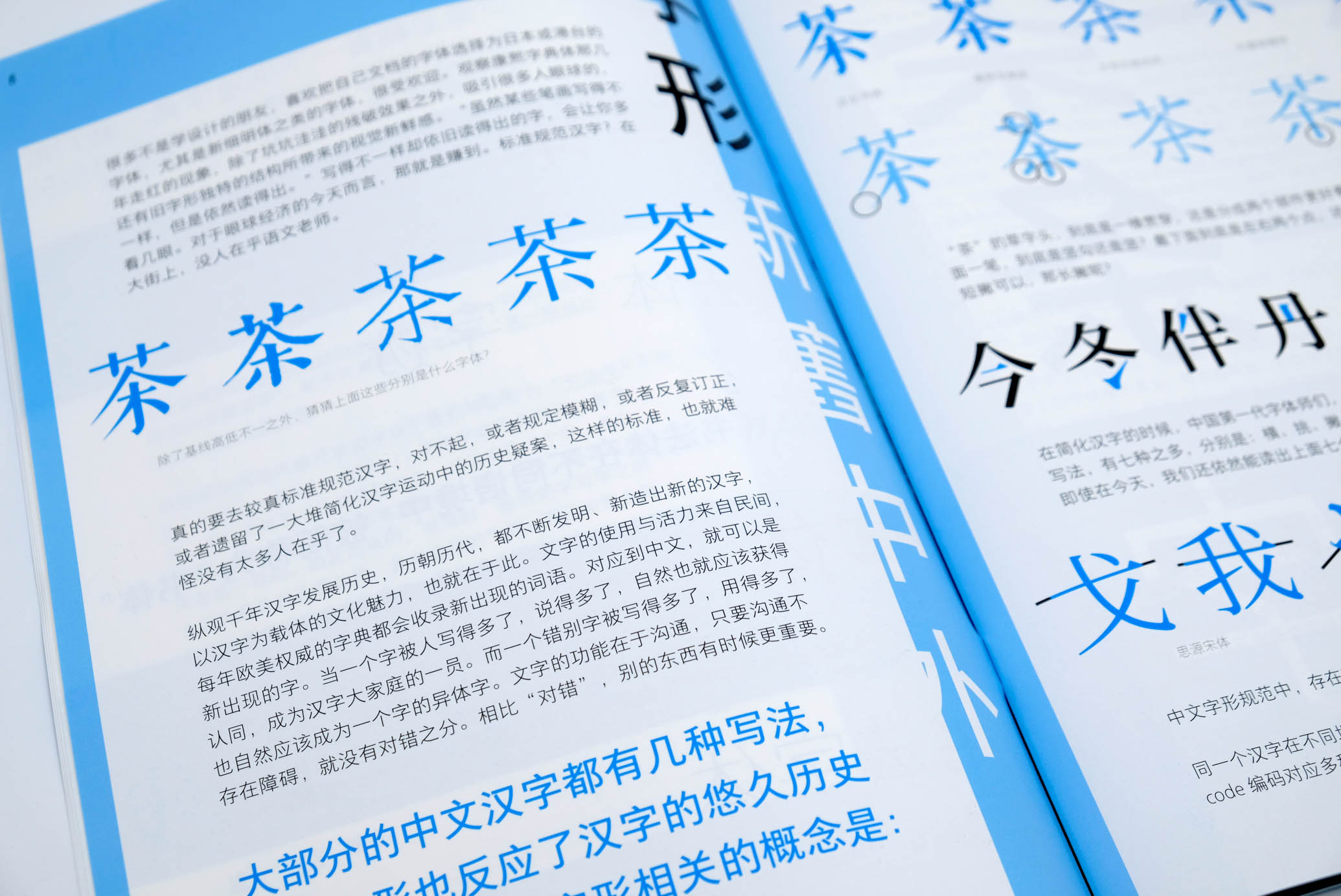
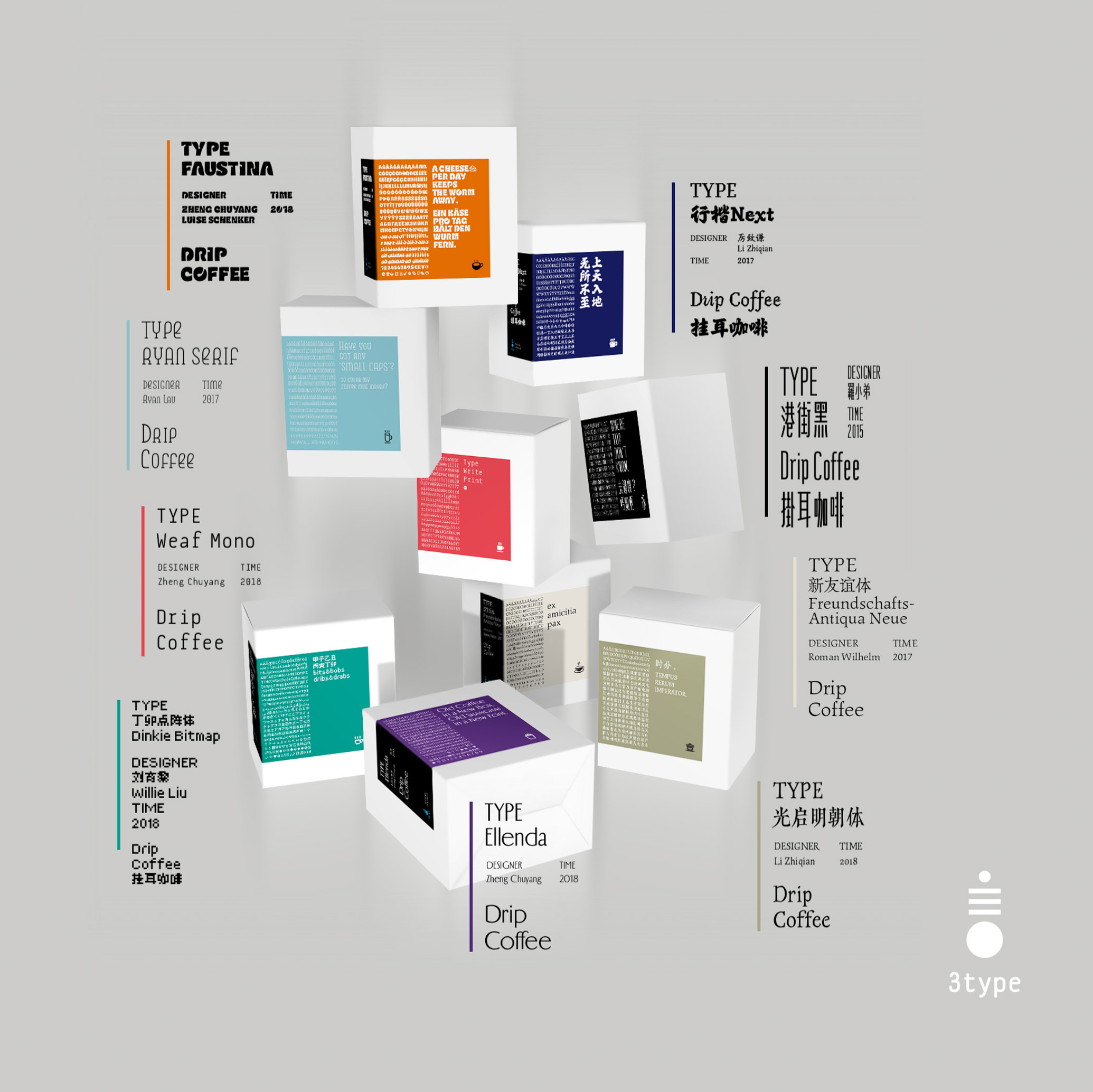
中文字体的这些问题,你想过吗?
如何透彻理解中文字形结构,正确选择合适的字体?
中文印刷字体的发展史,对当今数字字体有何影响?
宋、黑、仿、楷的字形特点怎样应用于实践?
复刻字体是如何创作的,对字体设计的意义是什么?
字面、轮廓、中宫、第二中心线……这些概念是什么,又该如何调整优化?
设计原创中文字体,该从哪里入手?
中文字体的西文部分应当如何匹配设计?
如何利用 Glyphs 软件优势开发中文字体?
中文字库制作是否有捷径可走?
中文排版如何设置看起来才是舒适的?
TypeSchool 和汉仪字库资深设计师朱志伟老师和刘宇老师,将为你一一释疑解惑,带着你走出原创字体的第一步,而对于有志参加「汉仪字体之星」的同学来说,此次课程更是一条不可多得的捷径。课程结尾更有人气主播 Éric Q. Liu 为大家带来久违的 TypeSchool 经典环节「文瀛讲坛」,此次加量版「文瀛讲坛」聚焦于中文排版,将大家在平时的工作和创作中可能遇到的字体排印相关问题一网打尽。
朱志伟老师 1971 年至 1991 年在北京外文印刷厂从事印刷活字雕刻工作,1996 年开始涉⾜字体设计,有多项字体设计作品成功开发为字库产品在社会上广泛使用,同年在日本森泽公司举办的国际印刷字体竞赛中「北魏楷书」获得铜奖,1999 年「铁筋隶书」获得该项赛事的评审委员奖。 2015 年加盟汉仪后设计开发「汉仪玄宋」,任职汉仪字库艺术总监、汉仪字体之星设计大赛评委, 并被北京服装学院设计学院聘为客座教授。
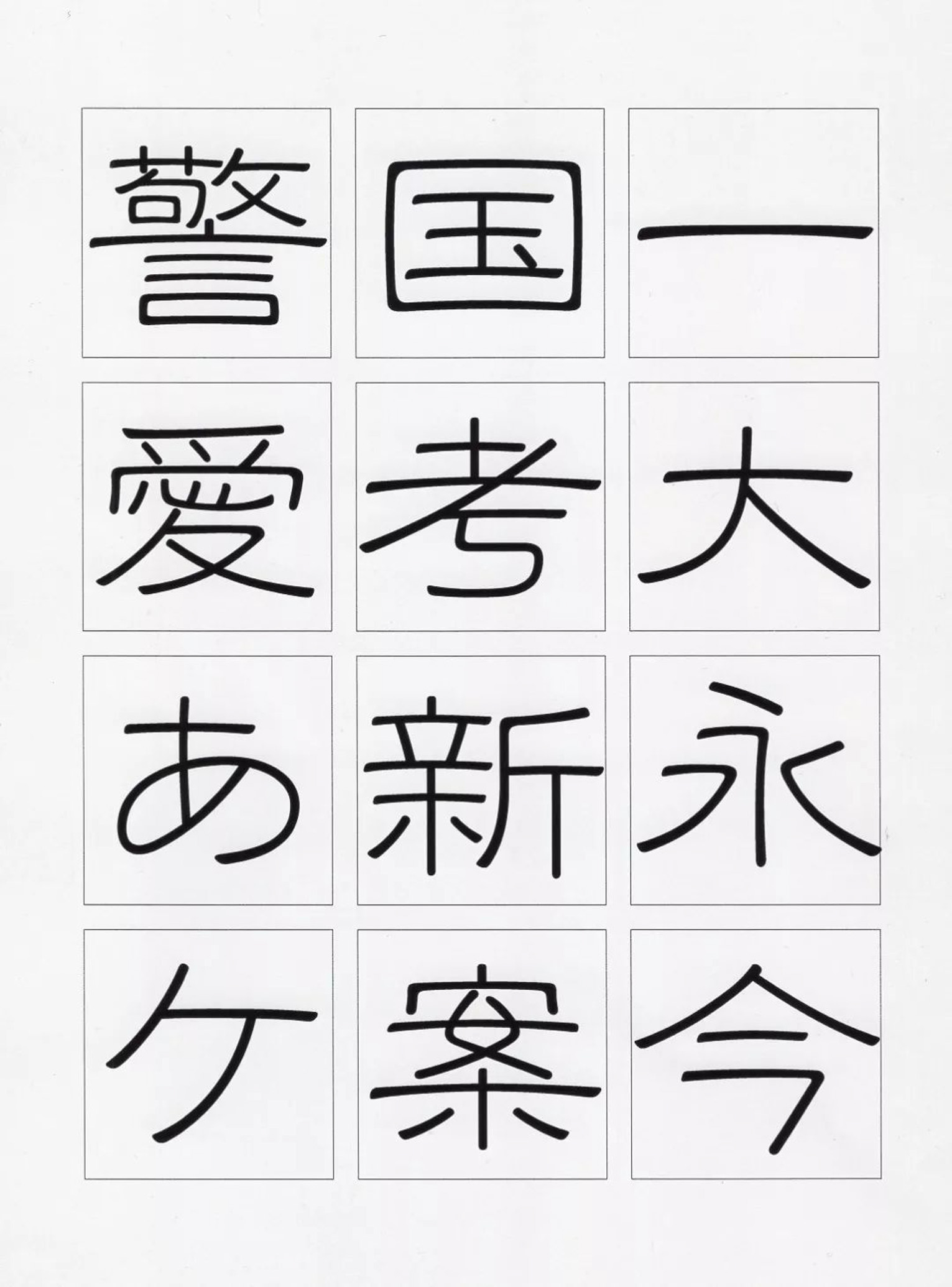
此次 TypeSchool 朱志伟老师将以多年行业经验和敏锐的眼光,帮助大家迅速掌握中文设计的要点,并有针对性地进行辅导。
刘宇毕业于北京服装学院视觉传达专业,现任汉仪公司高级定制项目组组长,同时身为SGDA 深圳市平面设计协会会员,ATypI 国际字体排印协会会员。刘宇曾负责多个定制字库项目,先后在阿丽达黑体定制项目、芬兰 Supercell 公司皇室战争游戏字体定制项目中任职中文主创设计师。先后创作了汉仪力量黑、汉仪跳跳体、汉仪乐喵体、汉仪帅线体、汉仪夏日体等字体。乐喵体推出后立刻引发了下载风潮,当年便荣获小米年度最受欢迎字体奖。在刷屏时代,为了满足市场越来越强烈的个性化需求,刘宇不断用创新字体丰富着视觉的表达。
凭借多年字体设计的经历,刘宇将会给大家带来更多激发字体设计创意的思路,以及如何从身边的方方面面寻找可以借鉴到自己设计中的灵感。
郑初阳是 3type 联合创始人之一,德国德绍包豪斯设计硕士,曾就职于欧洲顶尖的品牌设计公司 MetaDesign,服务过多家跨国公司。郑老师擅长在多文化语境中的开展平面与品牌设计,对多语言字体具有多年的研究与实践经验。
杨林青,著名旅法书籍、平面设计师,从事当代出版物的策划、编辑与设计工作,并致力于中西文字体的媒介应用和图形信息交流的研究。曾多次获得“中国最美的书”奖,第七届和第八届全国书籍设计艺术展社科类、文学类、教育类最佳书籍设计奖,2017 年年度亚洲卓越新闻奖“SOPA 卓越杂志设计奖金奖”。曾策划和参与《字体传奇——影响世界的 Helvetica》《平面设计中的网格系统》中文版的出版。2017年主编与设计《中文字体应用手册》。
杨老师可谓是 TypeSchool 的老朋友了,连续几年的中西文字体课都来做过讲座。这次我们有幸再次请到了杨老师,他在百忙之中将为我们带来「作为语言的设计」的讲座,解析中西文字体的选择、应用、建立系统、再到表达内容主题。同时杨老师还会跟同学们密切互动,从一个书籍设计师的角度,给出自己对于字体的独到见解。参与的同学们,可别忘记提前准备好杨老师的字体书请他签名哦!
Eric 在 Type is Beautiful 开设了关于中文排版的「孔雀计划」专栏,每篇洋洋洒洒一两万字,巨细靡遗地逐一分析目前排版的细节问题,逼死各种强迫症。这次「文瀛讲坛」中,Eric 不仅会亲自给大家划重点,还会从理论分析落实到大家日常的排版实践。字库的 OpenType 特性从哪里调用?使用 InDesign 和 Illustrator 进行中西文排版需要做怎样的设置、又有哪些技巧?一段 CSS 代码的利弊将要如何权衡?……种种问题,将带大家逐一解决。
大家平时用 Adobe 软件做排版,可无论 InDesign 还是 Illustrator,里面都是险象环生,稍不留神,就会一脚踏入大坑!Eric 已经将那些最让人头大的问题整理成了「InDesign 中文排版五大原则」让大家从此无惧深坑困扰!
如果没有电脑,平面设计师怎么工作?怎样编排字体?怎样在版面里插入图片?怎样运用色彩?设计稿做完了又如何让印刷机批量印刷?
今日,绝大部分的设计靠计算机软件完成,得益于它的迅捷,也受制于它的单一,更因为行业知识的断层,数字工具成为我们唯一的依赖。当我们渴望探索新的创作手法,当我们深入研究某种风格的来源,当我们意识到设计师与工艺材料之间的隔阂,当我们争论 AI 是否能代替创意工作者,当我们开始思考人的设计与创作活动的本质……我们无可避免地频频回望,期待从历史中寻找启迪。
这也许是纪录片 Graphic Means(《平面之道》)在去年一经推出就引起广泛反响的原因。这部有关前数字时代西方平面设计历史的纪录片,从上世纪五十年代直至九十年代、从热金属铸排机到激光照排、从手工剪贴到数字 PDF 文档,它探索了平面设计职业生产方式的发展。此次课程将与纪录片制作方合作,将它正式带到你的眼前。
第一天,全面了解中文字体设计的基本流程,临摹经典中文字体——宋体;
第二天,学习中文字体设计的理论知识,亲自动手做汉字间架结构的练习,临摹经典中文字体——黑体;
第三天,继续学习中文字体设计基础知识、创意字体的设计方法并绘制草稿,初识字体设计软件 Glyphs;
第四天,进一步学习 Glyphs 软件,在软件中绘制临摹的宋体黑体字并导出;著名书籍设计师杨林青将通过「作为语言的设计」与学员分享对字体设计的真知灼见。
第五天,完善自己的设计,学习使用软件制作字体家族(比如从粗到细的一套);学有余力的同学还可以利用可变字体和 Opentype 特性为自己的设计加分。
第六天,老师一对一辅导个人创意字稿制作之外,郑初阳还将带来讲座「中文里的西文设计」。
第七天,完成字体样张,进行作品的点评、颁奖和课后交流;汉仪字库将带来产品宣讲会,为大家解析爆款字体的创作历程。
第八天和第九天,人气主播 Eric 此次奉上专门针对中文排版需求的「文瀛讲坛」;汉仪字库携手制片方带来好评如潮的纪录片 Graphic Means 讲述前数字时代的平面设计以及汉仪星课堂。活动详情请及时关注 3type 和汉仪字库最新推送。